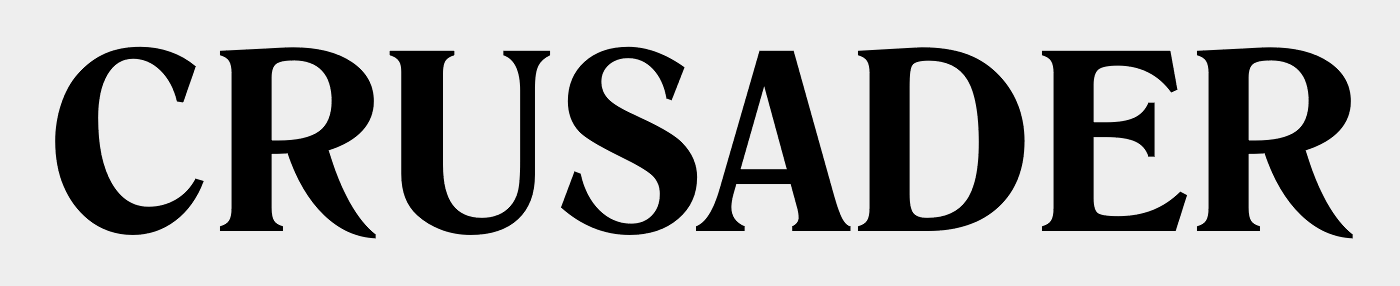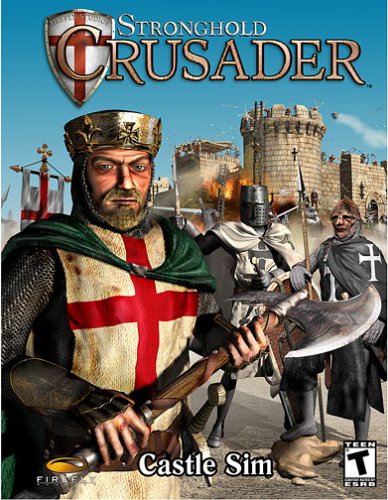
Suche Schrift von Stronghold Crusaders
Die Schrift kommt mir sehr bekannt vor ... Komm grade nicht darauf. Das Bild sieht aber sehr danach aus, als ob man für dieses Spiel auch die offizielle Anleitung irgendwo als PDF mit eingebetteten Schriften finden könnte. Also lassen wir eine typische Anfrage für solche Probleme los.
1) Wir werfen Google vor: "Stronghold Crusader Castle Sim file:PDF"
2) Das ergibt bei mir gleich als erstes Ergebnis die englische Anleitung:
3) In dem PDF sucht man dann die Schriften durch und findet die RomanaBT ... klimper ... schepper ... (Groschenfallgeräusche)
Die Romana wird aber nicht in dem Titel verwendet  …  :neenee:
Looking at the manual i'm convinced it is a custom (crap) job... Strokes and roundings are a bit odd comared to each other